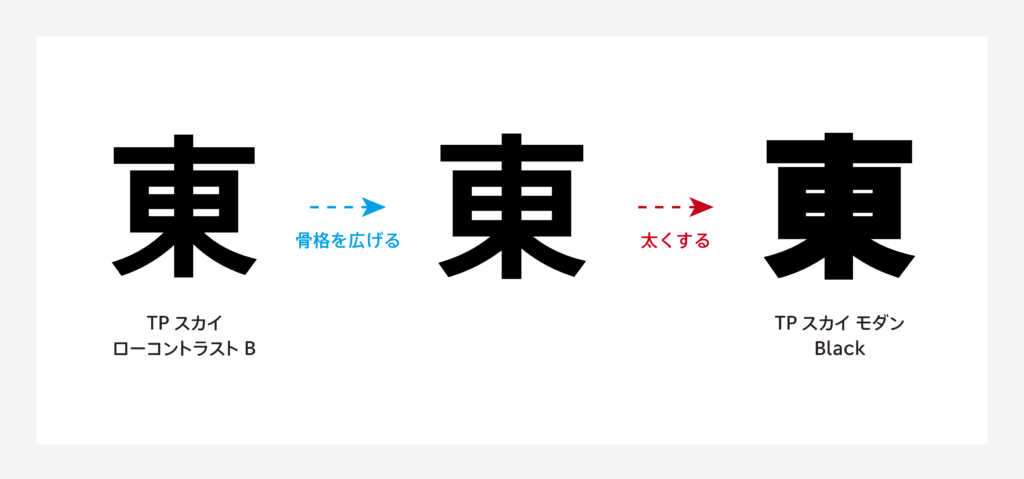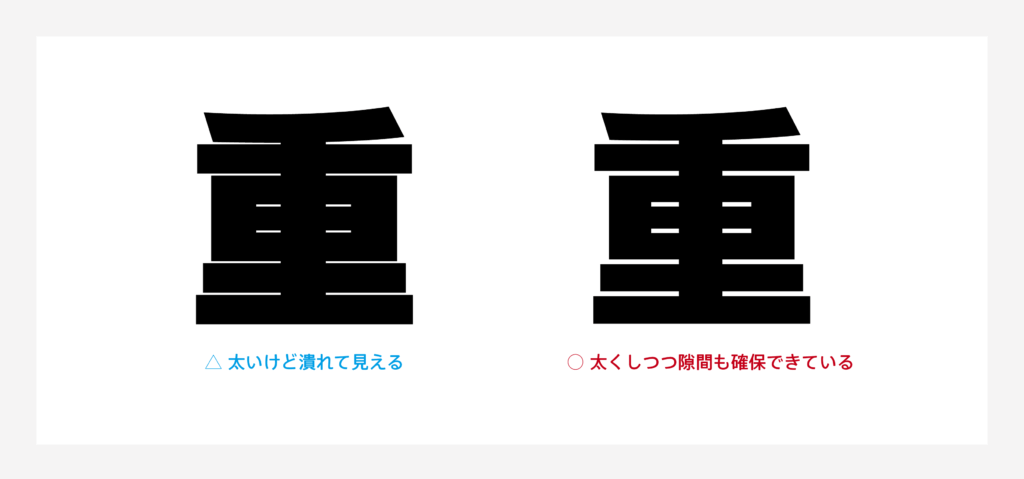
TPスカイ モダン開発ストーリー 01「あちらを立てればこちらが立たず」
TPスカイ モダンには、最初に極太のウエイト「Black」の制作に参加し、その次に「UL」を制作しました。ウエイトの高低差が一番激しい移行だったと思います。
自分がBlackに参加したタイミングでは、漢字制作がかなり進んでおり、既に全体のデザインルールができている状態でした。TPスカイ モダンの雰囲気を掴みつつ、Black特有の制約と戦いながら制作に臨みます。
上記の記事にもあるとおり、Blackの制作は、TPスカイ ローコントラスト Bから骨格を広げて筆画を太くする作業でした。ベースになる文字から、モダンらしさを出すために差をしっかりつける必要があります。
まずは骨格を広げて「モダンらしくする」。 そしてできるだけ「太くする」。
けれど、ただ太くしたり、骨格を広げすぎて「筆画同士の隙間」が埋まってはいけません。 筆画同士の隙間や、筆画の太さの数値がある程度決まっています。
さらに、なるべく「筆画同士の太細の差を控えめに」調整します。 そしてTPスカイ ファミリーとしての「デザイン方針に合っているか」。 そしてそもそも「組んだ時に全体の黒みが揃っているか」。
筆画同士の隙間を確保すると骨格の広げ方にも限界があるし、文字を太くして対応しようとすると他の文字の太さと揃わないし……と、参加したばかりの頃は「あちらを立てればこちらが立たず」の状態によく陥っていました。
たくさんの漢字を制作していくと、他の文字の太さとの揃い方が分かるようになり、先輩からも「ここを優先的に太くすると全体がしっかり太く見えるよ」というような、線の効果的な太らせ方も教えてもらったおかげで、スムーズに制作できるようになりました。